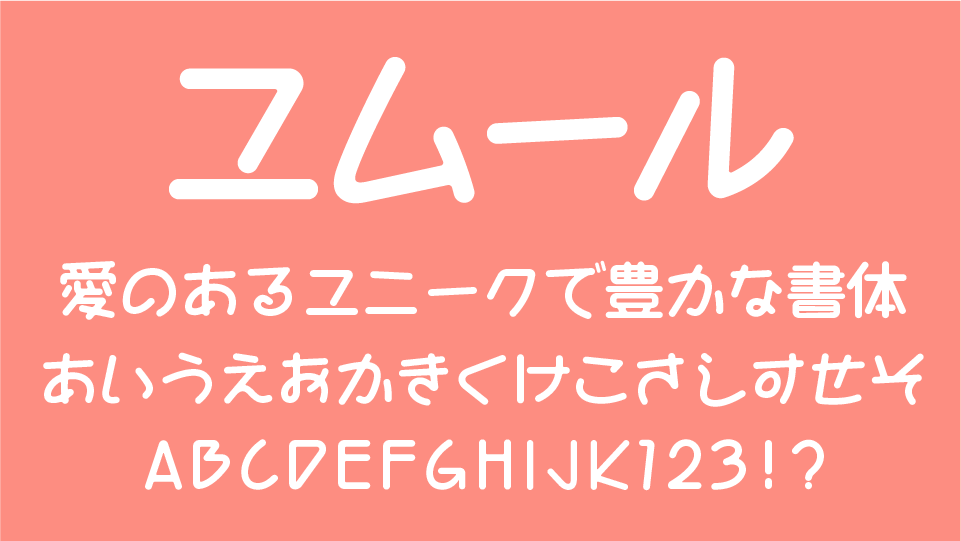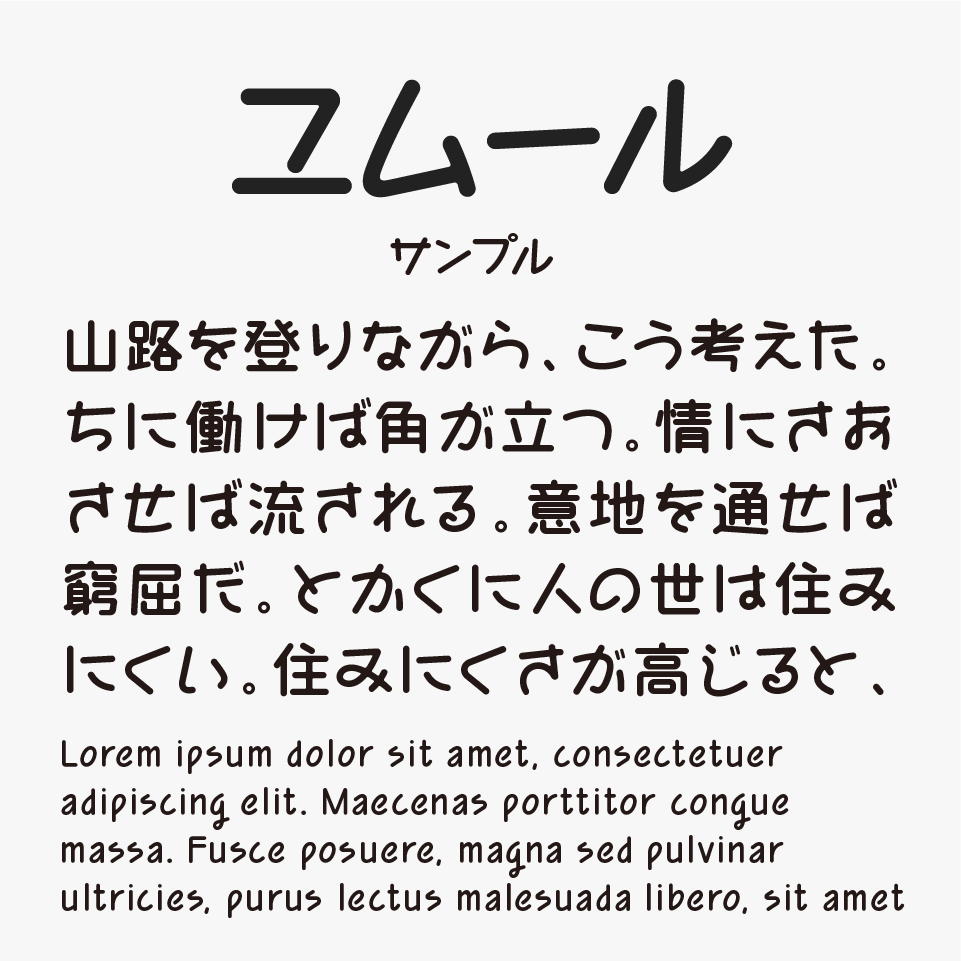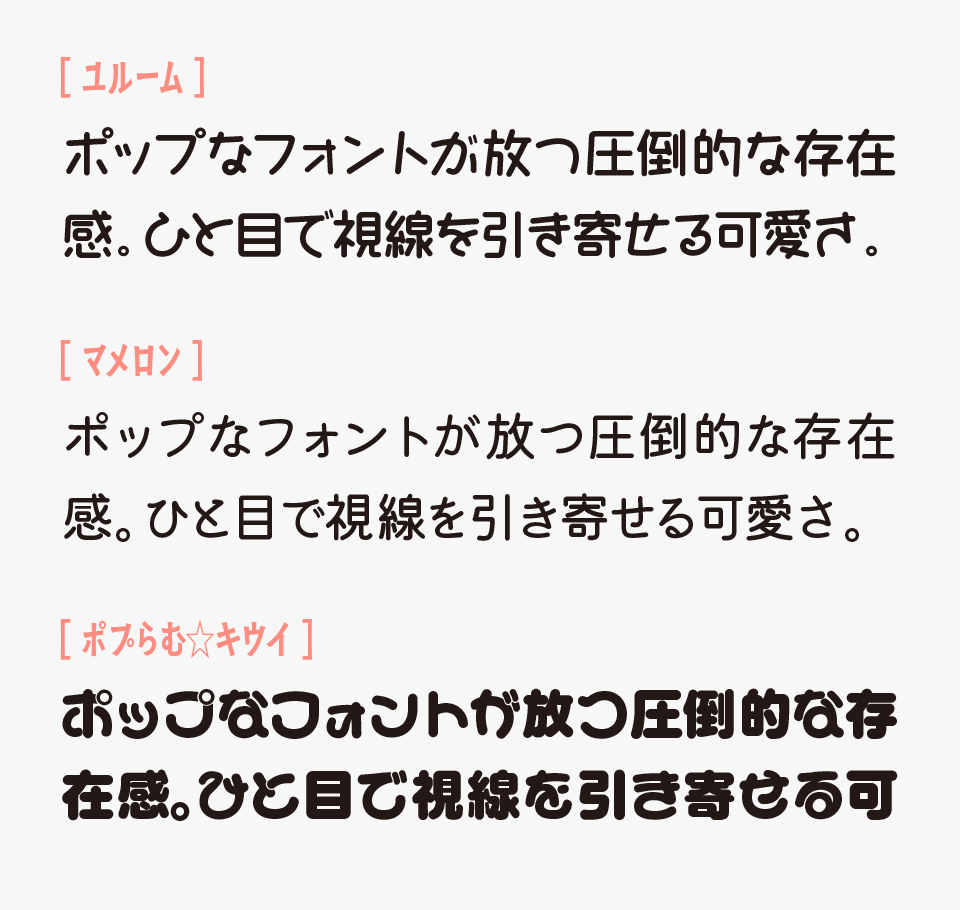
ユムール
ユムールフォントは、ラフに描いたマーカー文字のような軽やかさがあり、遊び心のあるポップな流れと、飾りすぎない直線的な線が組み合わさった可愛らしいデザインフォントです。
線の端にほんの少し丸みがあり、力を抜いた自然な筆圧によって、親しみやすさと抜け感が心地よく混ざり合っています。
ユムールフォントは、フォントメーカー「もじワク研究」が開発した「旧マメロンフォント」の可愛らしさにスポットを当てて制作されたデザインフォントです。
どこか懐かしさを感じる丸みや親しみやすい空気感を受け継ぎながらも、線の流れやバランスには新しさがあり、現代的な軽やかさも感じられるフォントに仕上がっています。
「もじワク研究」が開発した「マメロン」や「ポプらむ☆キウイ」のフォントと比較すると、ユムールフォントを非常に可愛らしくポップな仕上がりになっています。
収録文字は、ひらかな・カタカナ・欧文・数字・記号・JIS第一水準漢字(2965字)・JIS第二水準(200字程度)が収録されています。